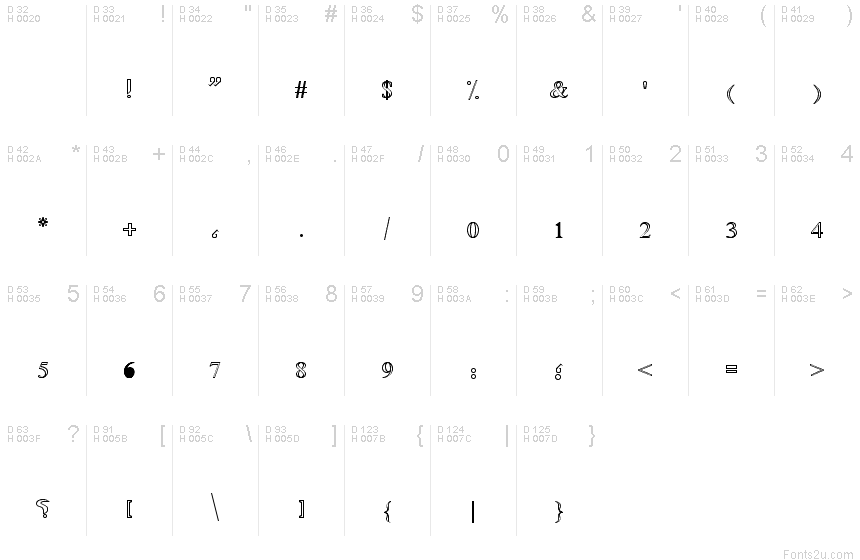
UL Noreen Shaded, darmowy arabski font z cieniowaniem od Urdulife, charakteryzuje się kaligraficznym przepływem przypominającym styl Nastaliq, gdzie litery zdają się układać w stosy i przesuwać diagonalnie wzdłuż linii. Cieniowanie to główny atut tego kroju: nadaje pociągnięciom rzeźbiarską, plakatową głębię, podczas gdy zwarte połączenia i charakterystyczny rytm sprawiają, że pismo pozostaje formalne i wyraziste.
Doskonale nadaje się do nagłówków zaproszeń, okładek książek w języku urdu lub arabskim, tytułów religijnych, plakatów kulturowych oraz krótkich projektów identyfikacji wizualnej, gdzie darmowy font ma zapewnić silny, tradycyjny klimat bez wrażenia prostoty. Użyj go do kart tytułowych, nagłówków lub krótkich cytatów, gdy chcesz, aby kaskadowy ruch i wbudowany cień wykonały większość pracy wizualnej za Ciebie.